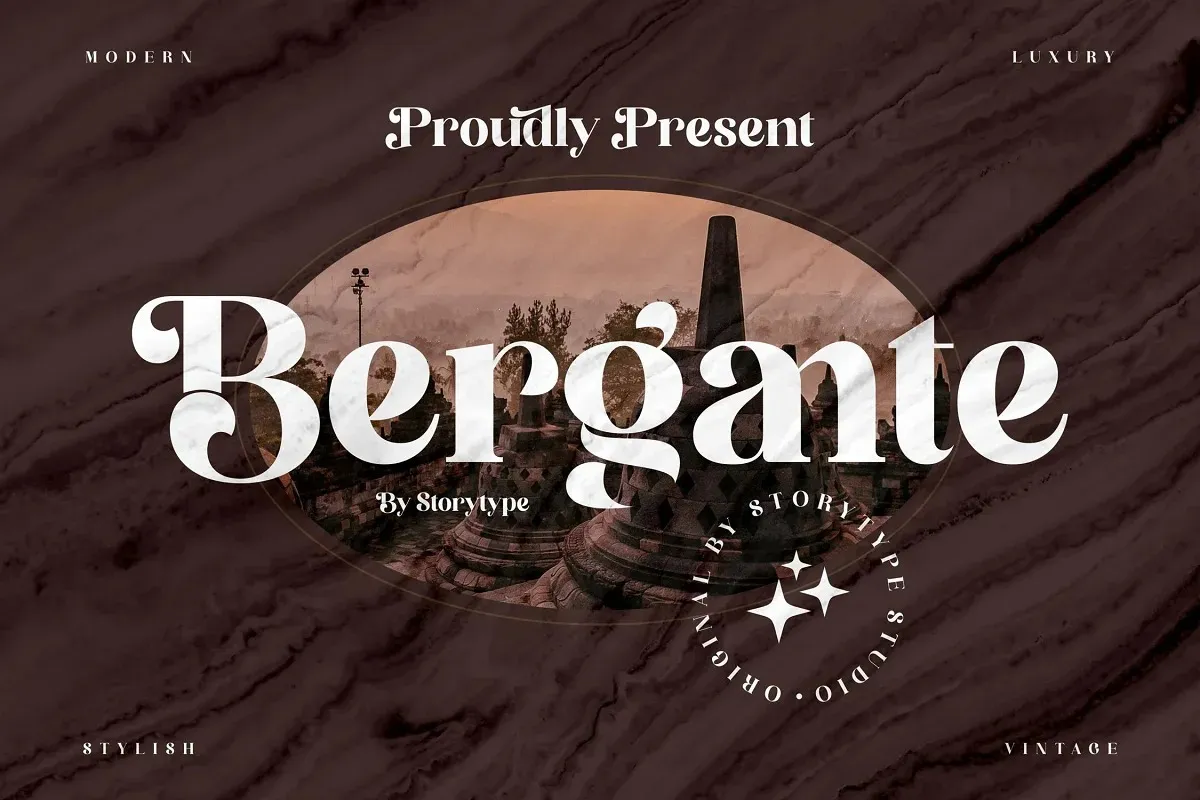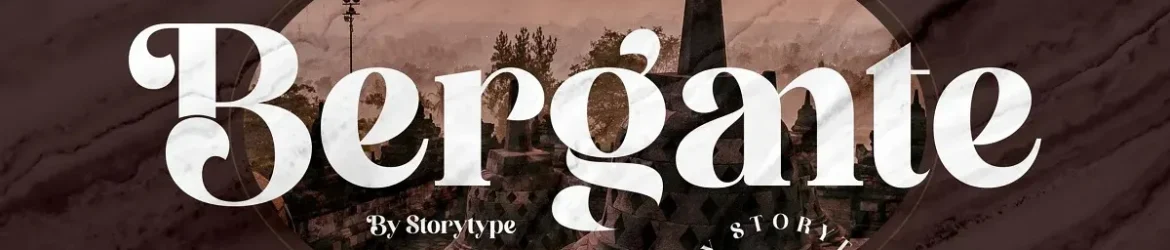
Bergante Font – Download Grátis
A Bergante Font é uma elegante tipografia serifada que combina formas geométricas com detalhes curvos orgânicos para criar um tipo único e singular. Ideal tanto para marcas de luxo ou roupas de grife, quanto para o design de livros, filmes ou revistas, a fonte Bergante atinge perfeitamente essa missão ao oferecer uma identidade visual sólida e sofisticada. Ela é especialmente adequada para nomes de marca que desejam transmitir uma atmosfera de elegância, proporcionando um toque único e inovador em qualquer projeto. Seja em logotipos impecáveis ou design editorial refinado, a Bergante Font traz uma pitada de modernidade e sofisticação, tornando-a uma opção indispensável para criadores atentos às últimas tendências de design.